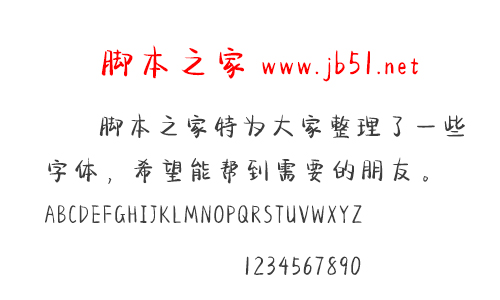
字語(yǔ)戀花體筆畫(huà)質(zhì)樸,巧妙的將傳統(tǒng)書(shū)法與現(xiàn)代審美相結(jié)合,整體風(fēng)格淡雅娟秀且文藝氣息十足。適用于文藝類(lèi)的書(shū)刊、品牌廣告和產(chǎn)品包裝設(shè)計(jì),以及社交網(wǎng)絡(luò)的個(gè)性化用字,歡迎喜歡字語(yǔ)戀花體的朋友前來(lái)下載使用。